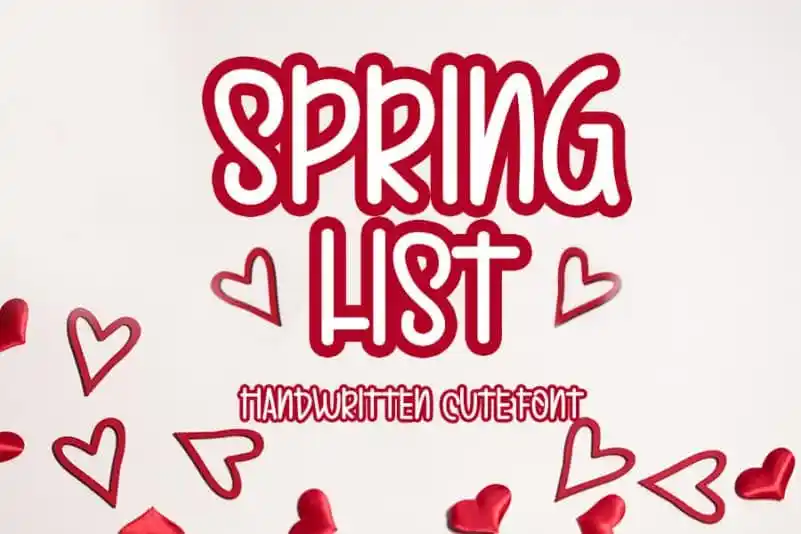
Spring List Display Font – Download Grátis
A fonte Spring List Display é uma criação única que se destaca por ser tanto elegante quanto moderna. Ela mantém sua influência clássica do gago, ao mesmo tempo empenhada e atual. Este tipo de fonte é perfeito para designers criativos, oferecendo flexibilidade para um leque amplo de ideias, desde os selinhos até as títulos, além dos papéis de carta e materiais de escrita. Spring List Display é ideal tanto para aquelas pessoas que desejam manter uma aparência clássica quanto para aqueles que buscam algo mais contemporâneo. Esta fonte será um recurso valioso para qualquer designer buscando adicionar personalidade a seus trabalhos visuais.